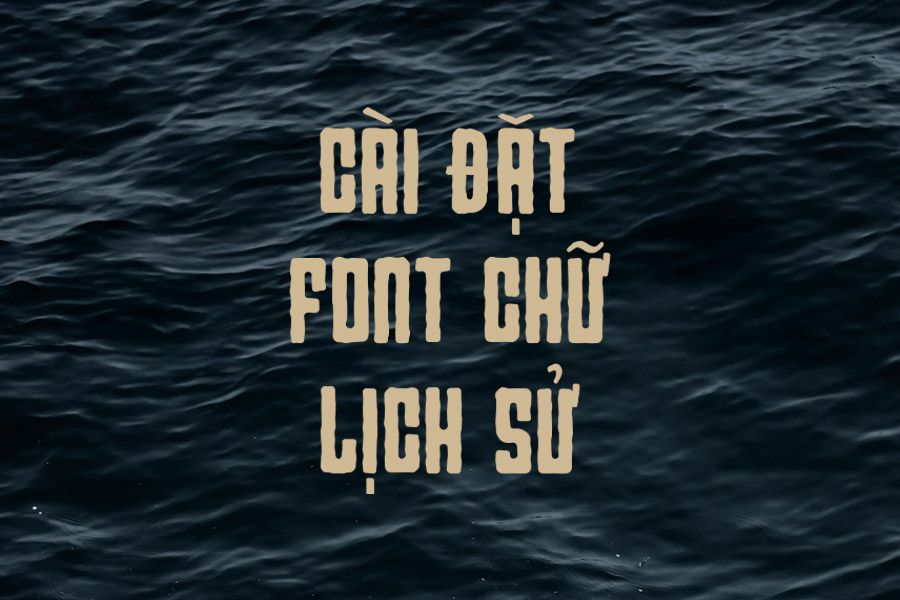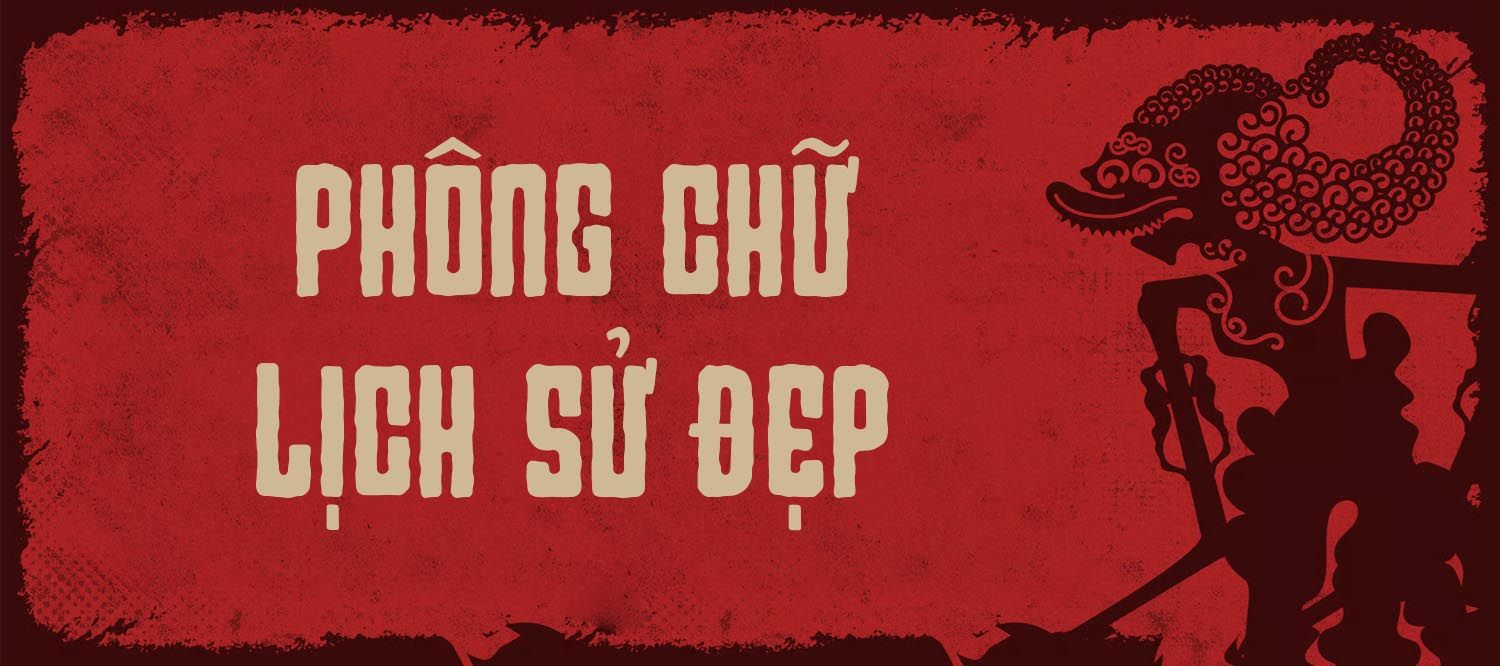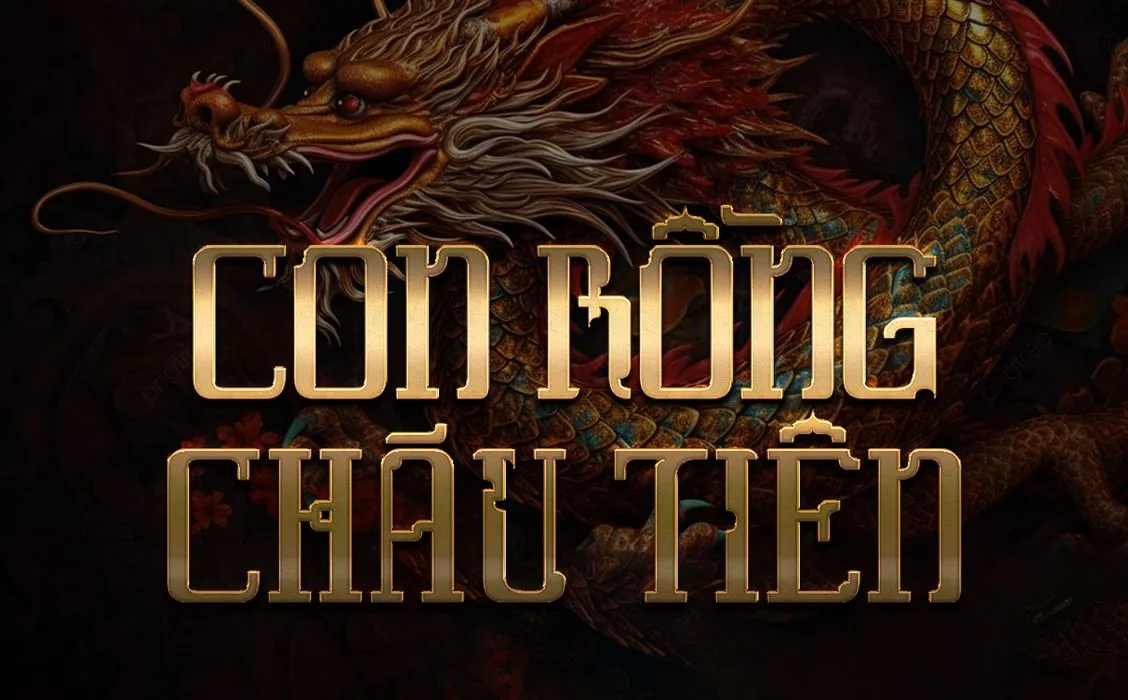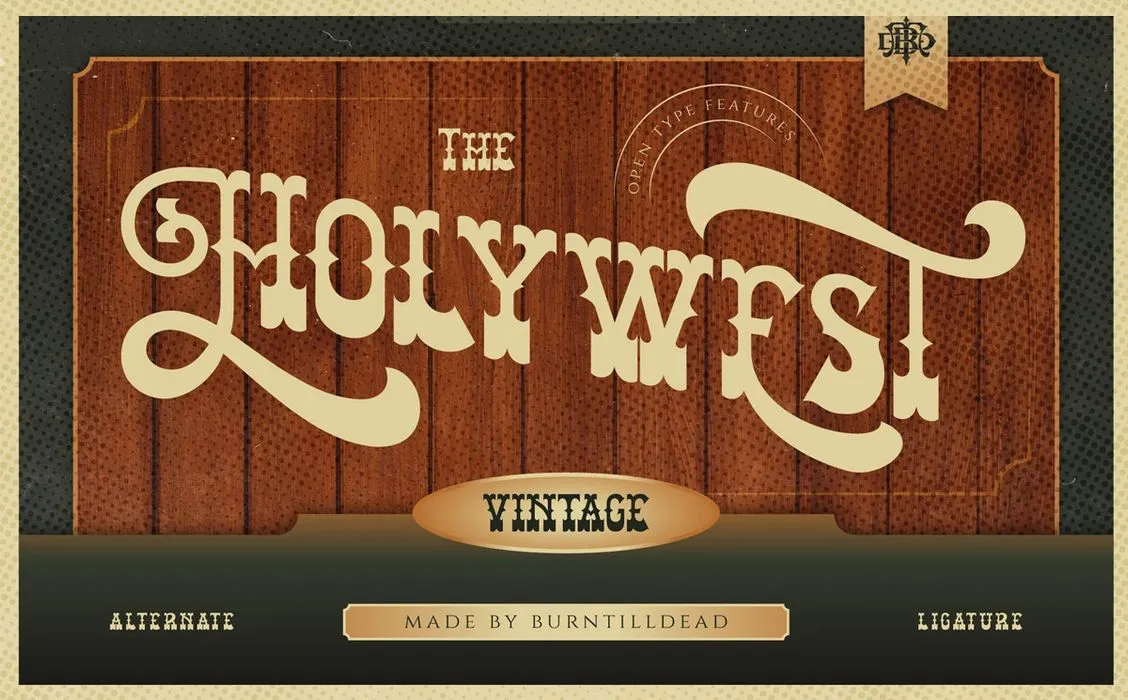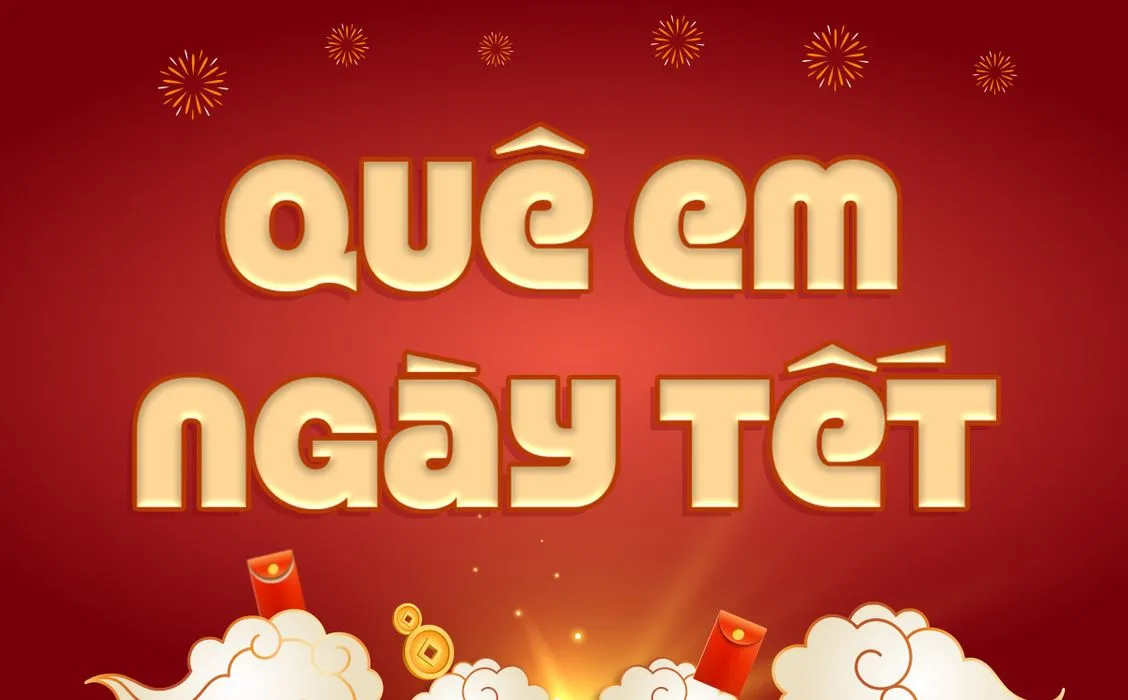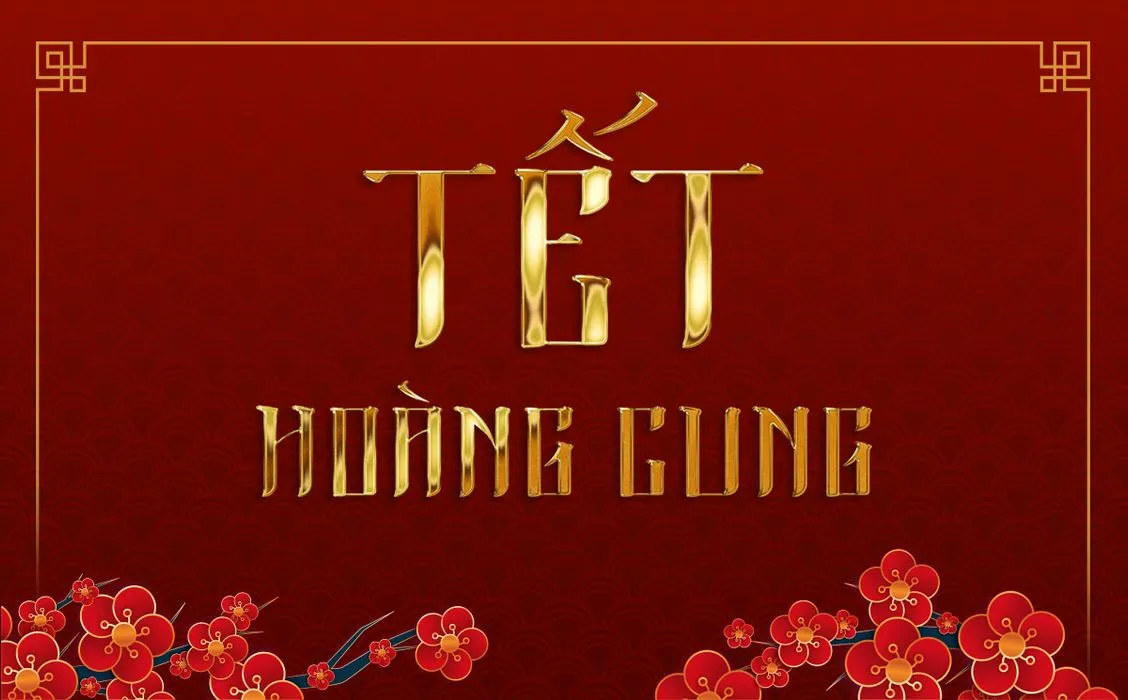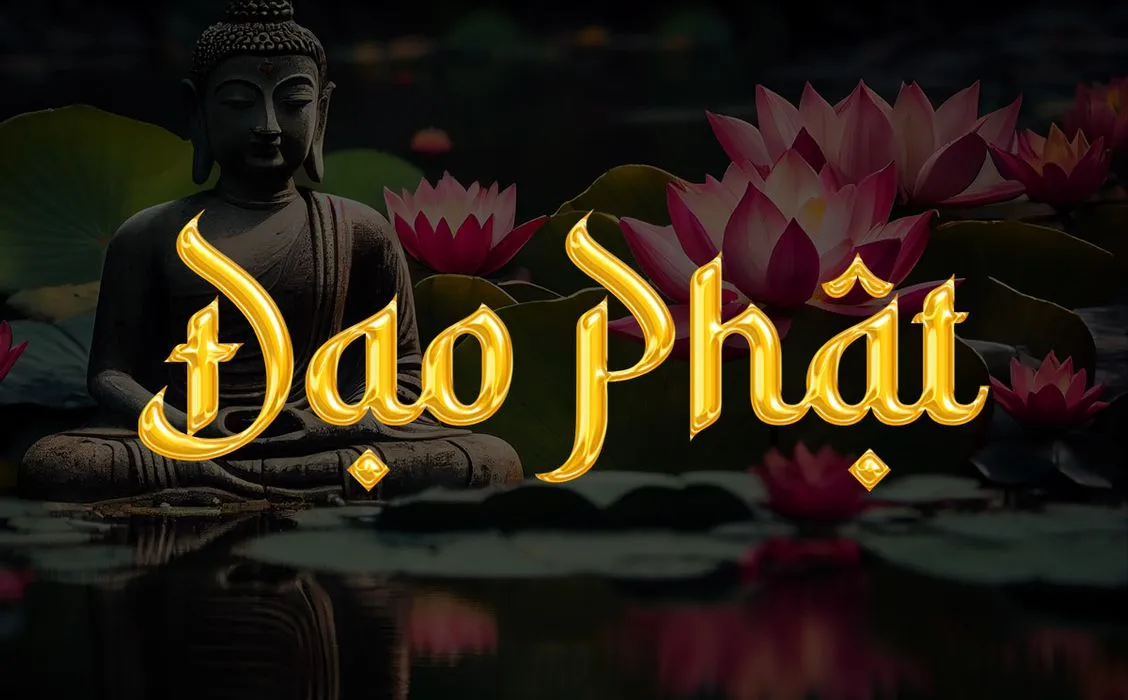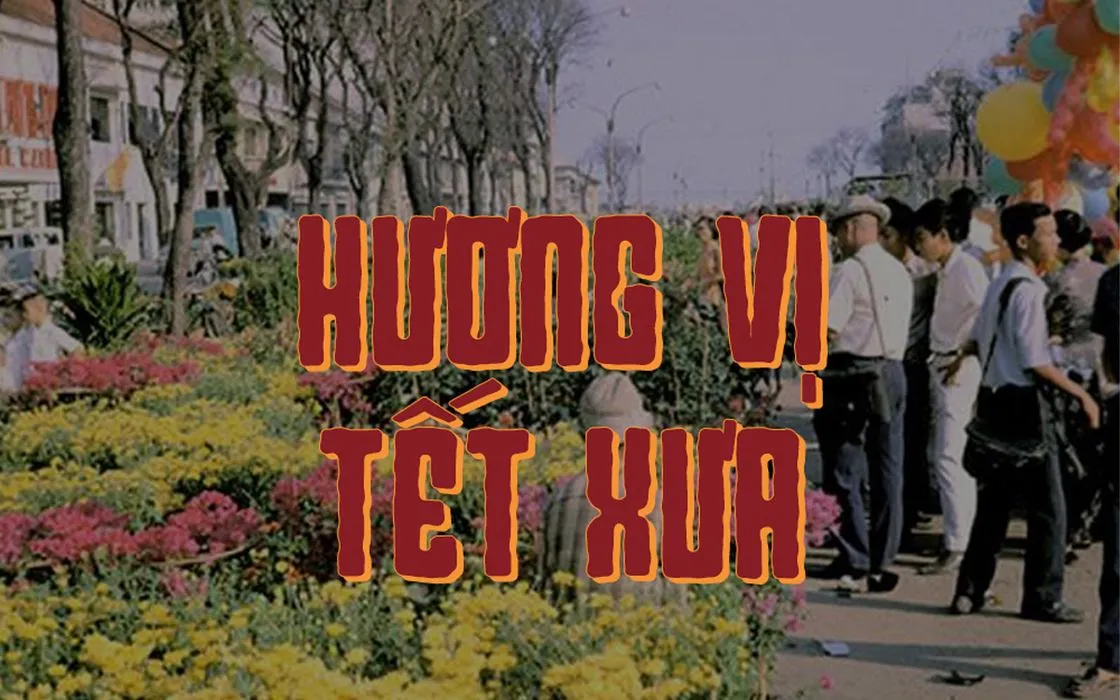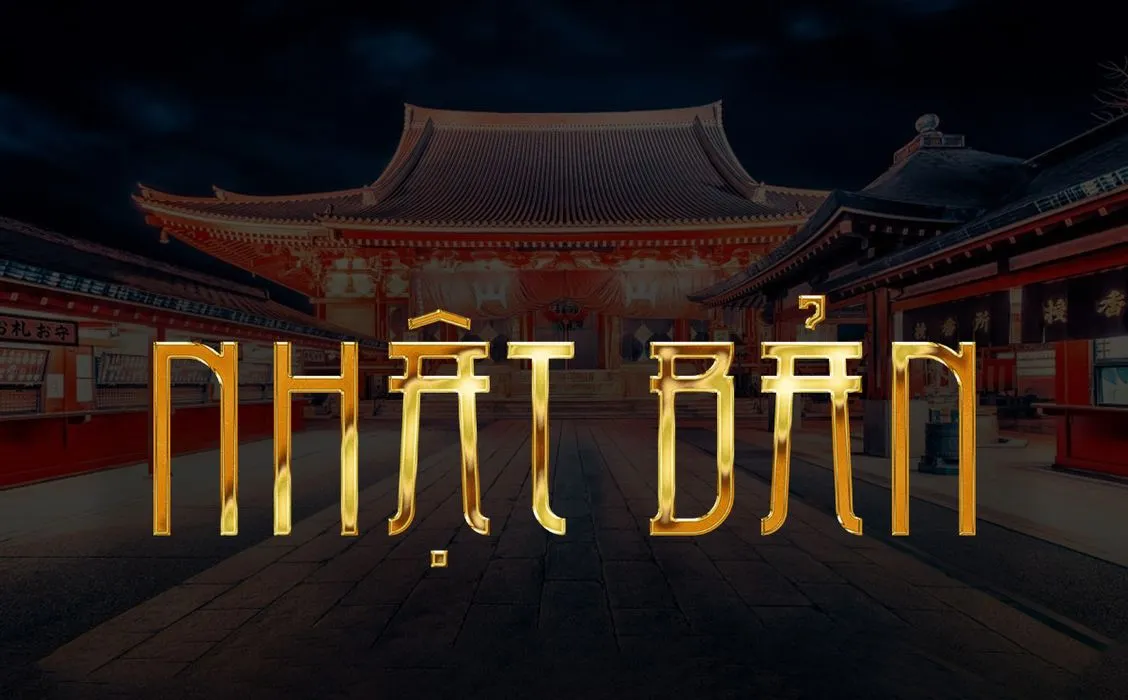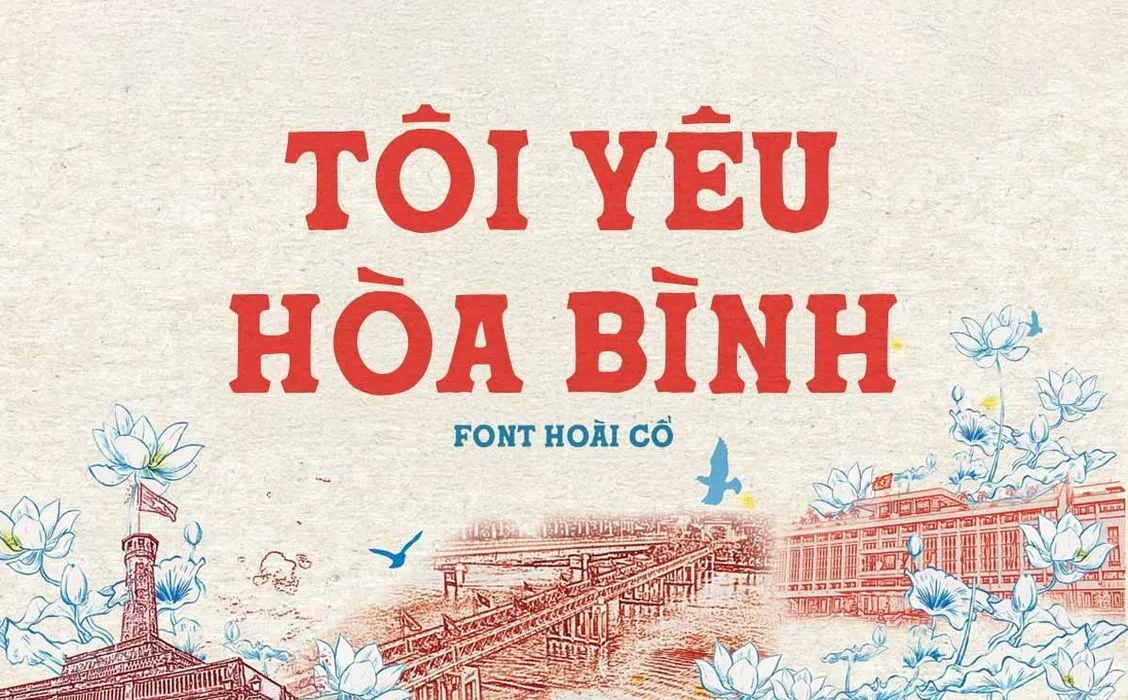
Tổng Hợp 17+ Font Chữ Lịch Sử Việt Hóa Mộc Mạc và Xưa Cũ
1. Giới thiệu tổng quan
Font chữ lịch sử là những kiểu chữ tái hiện tinh thần và phong cách của các giai đoạn quá khứ, thường thấy ở Serif cổ điển, Script viết tay hay Retro gợi nhớ thời kỳ công nghiệp. Khác với font hiện đại thiên về tối giản, chúng giàu chi tiết và cảm xúc, giúp gợi ký ức hoài niệm và tạo bản sắc riêng. Trong thiết kế ngày nay, nhiều thương hiệu chọn phong cách này để tạo sự khác biệt và gắn kết với giá trị văn hóa. Không chỉ mang lại vẻ đẹp thẩm mỹ, font chữ lịch sử còn góp phần bảo tồn và truyền tải ký ức đến thế hệ trẻ. Khi xuất hiện trong poster, bảo tàng hay lễ hội, chúng vừa thu hút ánh nhìn vừa khơi gợi niềm tự hào.
Để bạn dễ dàng lựa chọn và ứng dụng, dưới đây là danh sách 17 font chữ lịch sử tiêu biểu nhất.
2. Danh sách 17+ font chữ lịch sử Việt hóa đẹp
1. Font chữ Tết cổ truyền TH Hoaico – Hoài cổ & Ấn tượng
TH Hoaico gợi nhớ không khí Tết xưa với những đường nét uyển chuyển và mềm mại, được tối ưu để ứng dụng trong thiết kế số. Font này đặc biệt phù hợp khi sử dụng trong thiệp chúc mừng, banner Tết hay bao bì sản phẩm mùa lễ hội, tạo nên sự sang trọng và gần gũi. Nhờ sự kết hợp giữa yếu tố truyền thống và tính thẩm mỹ hiện đại, TH Hoaico giúp designer tái hiện trọn vẹn nét đẹp văn hóa Việt trong từng con chữ.
2. Font chữ phong cách hoài cổ TH - HC Calvous Việt hóa
Font TH – HC Calvous trong ảnh mang đậm dấu ấn font chữ lịch sử, với những đường nét vuông vức, dày dặn và cân đối. Phong cách hoài cổ này gợi nhớ đến các áp phích, bích báo và biển hiệu thời bao cấp, tạo cảm giác mạnh mẽ nhưng gần gũi. Đây là lựa chọn lý tưởng cho thiết kế poster, banner sự kiện văn hóa và các dự án tái hiện ký ức lịch sử.
3. Font chữ lịch sử TH Juggernaut – Mạnh mẽ & Retro
TH Juggernaut gây ấn tượng với những block chữ dày, vuông vức và mạnh mẽ, gợi cảm giác vững chãi và quyền lực. Phong cách retro kết hợp yếu tố lịch sử khiến font này phù hợp cho các poster sự kiện, banner triển lãm hoặc ấn phẩm quảng bá di sản. Sức hút của Juggernaut nằm ở khả năng tái hiện bầu không khí công nghiệp và hoài cổ, vừa trang nghiêm vừa nổi bật.
4. Font chữ cổ điển TH Morucas – Vintage & Sang trọng
TH Morucas mang phong cách vintage cổ điển, với những đường cong tinh tế và serif thanh thoát. Font này gợi nhớ đến typography báo chí, quảng cáo châu Âu thế kỷ XX, thích hợp dùng trong tiêu đề tạp chí, poster hoài cổ hoặc thiết kế thương hiệu mang tính nghệ thuật. Nó kết hợp hoàn hảo giữa sự sang trọng và sự gần gũi của phong cách retro.
5. Font chữ Trung Hoa TH China 1 – Cổ điển & Trang nghiêm
TH China 1 được lấy cảm hứng từ nghệ thuật chữ Hán cổ, với nét chữ cứng cáp, vuông vức và mạnh mẽ. Phong cách này gợi đến kiến trúc, thư pháp và văn hóa Trung Hoa truyền thống, tạo cảm giác uy nghiêm và quyền lực. Font đặc biệt phù hợp cho poster phim cổ trang, banner lễ hội văn hóa hoặc thiết kế mang yếu tố Á Đông.
6. Font chữ chủ đề lịch sử TH Lichsu (3 font) – Trang nghiêm & Hoài cổ
Bộ font TH Lichsu mang đậm màu sắc lịch sử và truyền thống. Font chữ mang một đặc điểm riêng uy nghiêm gợi nhớ văn bản cổ đậm chất hoài niệm. Nhờ sự đa dạng này, bộ font trở thành công cụ lý tưởng cho các dự án cần tái hiện không khí lịch sử, đặc biệt trong thiết kế poster bảo tàng, triển lãm, banner sự kiện văn hóa.
Tác giả gốc: Chưa rõ
Việt hóa: Team TH
7. Font chữ cao SVN Calama – Thanh mảnh & Retro
SVN Calama mang thiết kế chữ cao, thanh mảnh và cân đối, mang đến cảm giác vừa retro vừa hiện đại. Font này phù hợp khi sử dụng trong các tiêu đề poster, tạp chí, hoặc giao diện kỹ thuật số cần sự tinh tế mà vẫn hoài cổ. Điểm nổi bật của Calama là khả năng tạo cảm giác trang nhã nhưng không kém phần nổi bật, nhờ đó phù hợp với nhiều phong cách thiết kế khác nhau.
Tác giả gốc: Ben Karamyan
Việt hóa: Team SVN
8. Font chữ lịch sử Nhật Bản TH Nhật Bản 1 – Sắc nét & Truyền thống
TH Nhật Bản 1 tái hiện tinh thần của thư pháp Nhật Bản với các nét chữ mạnh mẽ, sắc sảo và uyển chuyển. Font gợi đến không khí lễ hội và di sản văn hóa Nhật, làm nổi bật vẻ đẹp Á Đông trong từng đường nét. Đây là lựa chọn lý tưởng cho các thiết kế poster phim, banner sự kiện Nhật Bản hoặc những dự án cần phong cách cổ trang độc đáo.
Tác giả gốc: Chưa rõ
Việt hóa: Team TH
9. Font chữ cổ trang Chinese Prodigy – Mạnh mẽ & Cổ điển
Chinese Prodigy mang phong cách thư pháp cổ trang Trung Hoa với những nét bút lông cứng cáp và đầy khí chất. Font này đặc biệt phù hợp cho poster phim, bìa truyện, áp phích sự kiện văn hóa hoặc thiết kế liên quan đến lịch sử cổ đại. Với tính thẩm mỹ độc đáo, Chinese Prodigy mang lại sự uy nghiêm và mạnh mẽ cho bất kỳ dự án nào.
5. Kết luận
Font chữ lịch sử mang lại giá trị vượt thời gian: vừa bảo tồn văn hóa vừa làm giàu cảm xúc thị giác cho thiết kế hiện đại. Chúng giúp các dự án không chỉ đẹp về hình thức mà còn có chiều sâu, kết nối quá khứ với hiện tại và tương lai.